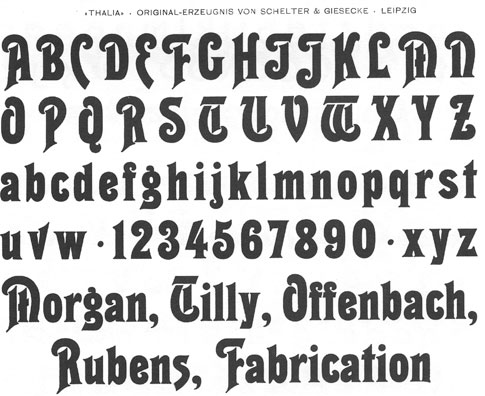
Schrift der "Inside Llewyn Davis"-LP
Noch eine Geschichte am Rande: Ende der 1960er Jahre
erlebte die Thalia ein Revival, weil die populäre Zeitschrift
»twen« sie verwendete. Ihr Grafik-Designer war
Willy Fleckhaus (wenn mich meine Erinnerung nicht sehr täuscht...)